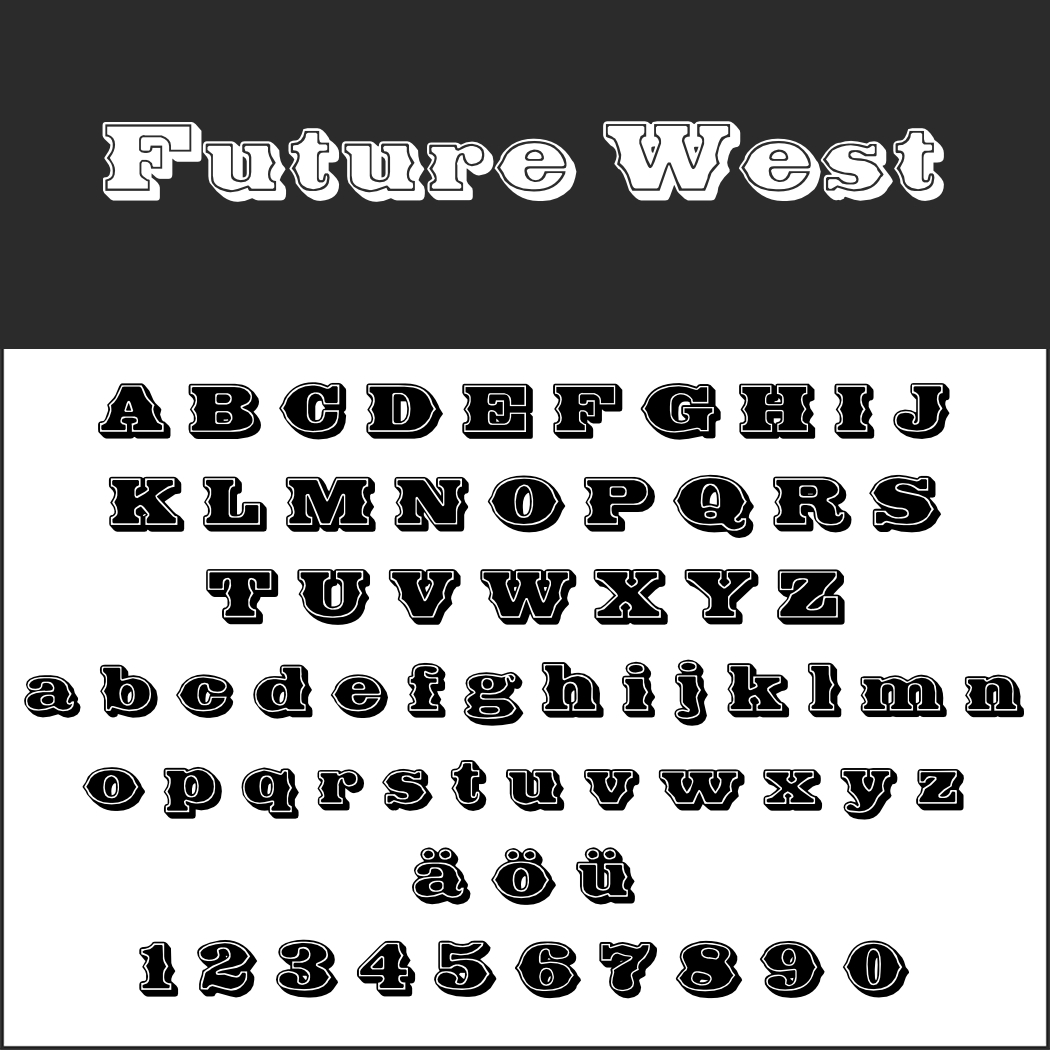
Western-Schriftarten
Eine Western-Schriftart passt nicht unbedingt nur, wenn es um Cowboys und Indianer geht. Sie eignet sich auch für Abenteuer-Freizeiten, Partys, Outdoor-Zubehör und einiges mehr. Allen gemeinsam ist zudem ein Hauch von Nostalgie.
Western SchriftartCamp Fire
Die aus „Holz genagelten“ Buchstaben lassen uns an Western-Comics denken – Fähnlein Fieselschweif im Ferienlager oder so ähnlich.
DS Roundup
Die Schrift ist denen auf den legendären Wanted-Plakaten nachempfunden.
Western SchriftartEdmunds
Dieser Cowboy-Font lebt wie DS Roundup von seinen aufdringlichen Serifen.
Future West
Mit Schatten und Kontur eignet sich Future West in erster Linie für Poster und Plakate.
Western SchriftartMarlboro
Der Geruch von Freiheit und Abenteuer: Das verkörperte die Werbefigur der gleichnamigen Zigarettenmarke. Fast ebenso berühmt wie der Marlboro Man ist die dazugehörige Schrift.
Nandaka Western
„Nandaka“ stammt aus dem Sanskrit und bezeichnet das Schwert des Hindu-Gottes Vishnu. Der danach benannte Font stammt aus Japan.
North Face
Die 3D-Buchstaben wirken, als hätte sie der Wind durchgepustet, was ihnen etwas Verwegenes verleiht.
Western SchriftartOld Town
Mit Old Town haben wir noch einmal eine andere Version der Wanted-Plakatschriften.
Porter Sans Block
Hier wird nicht gekleckert, sondern ordentlich geklotzt. Der raumgreifende 3D-Font eignet sich vor allem für Plakate.
Western SchriftartRancho
Eine Pinselschrift, die nicht nur Wildwest-Flair, sondern auch gute Laune ausstrahlt. Mehr in diesem Stil finden Sie unter Kalligraphie-Fonts und Brush Fonts.
Rio Grande
Kurze Schlagwörter kommen mit dieser Slab-Serif-Schrift im Western-Stil ganz groß raus.
Showboat
Wie Western von gestern: Mit Showboat leben die 1910er und 1920er Jahre wieder auf.
Smokum
Die konstrastreiche Serifenschrift macht sich gedruckt sehr gut, funktioniert aber auch auf Bildschirmen.
Western SchriftartVanilla Whale
Das Auffallendste an diesem Font sind die Balken über und unter den Kapitälchen. Danach kommen die „Western“-Serifen.
Wooden Nickel NF
Die Western-Assoziation ist bei diesem Font nicht so stark ausgeprägt. Er erinnert an Jugendstil und die 1950er Jahre.
• Besonderheit: keine Großbuchstaben, keine deutschen Sonderzeichen
• Design: Nick Curtis